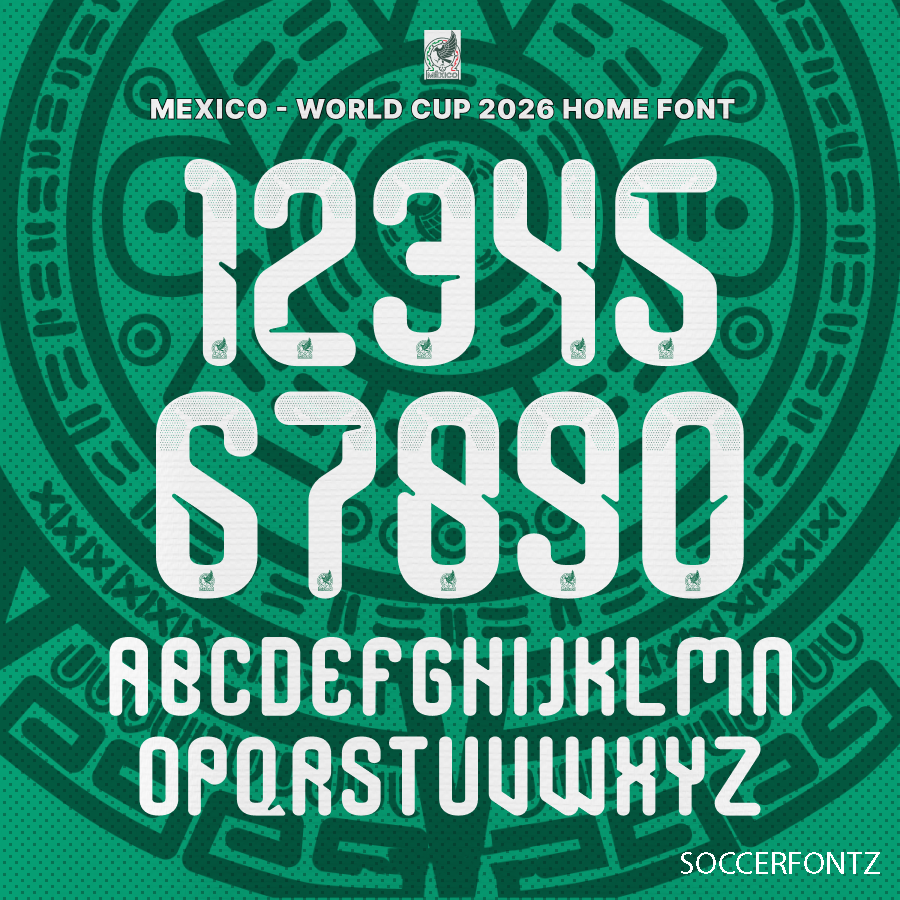
Características y beneficios destacados
La TIPOGRAFÍA MÉXICO – MUNDIAL 2026 ha sido cuidadosamente desarrollada para ofrecerte máxima versatilidad. Entre sus características principales, incluye:
- Números del 0 al 9 y un alfabeto completo con letras en mayúscula de la A a la Z.
- Glifo exclusivo de la cresta nacional para un toque auténtico y único.
Gracias a su diseño actualizado y detallado, esta tipografía cumple con las demandas del diseño moderno, haciéndola ideal para cualquier proyecto relacionado con el Mundial 2026, desde campañas publicitarias hasta personalización de productos.
Se incluye también un conjunto completo de caracteres, con números del 0 al 9 y un alfabeto exclusivamente en mayúsculas. Como detalle adicional, el glifo de la cresta nacional te permitirá añadir un toque auténtico a tus proyectos, destacándote entre tu competencia.